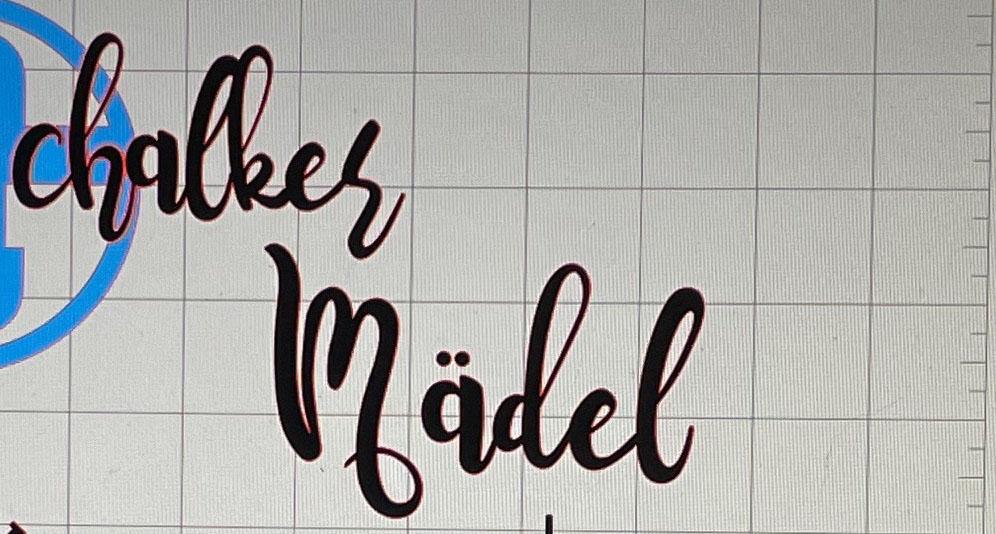
Hilfe bei Schriftart (Schalker Mädel)
angehängtes Bild ist Teil von meinem eigenen Entwurf. Leider ist mir der Rechner abgeraucht und ich komme nicht mehr auf die Daten der Festplatte, ich möchte es nachbauen, finde aber die Schriftart nicht. Whatthefont und Co waren nicht hilfreich.
Vielleicht könnt ihr Sie ja identifizieren :-)
Ja die sieht sehr passend aus :-)
Bei dem G vermute ich die Rockwell dahinter.
A, F und L passen auch. Die Rockwell wir bei einigen MS-Produkten mitgeliefert. Das passt auch … zum abgerauchten Rechner. 😱